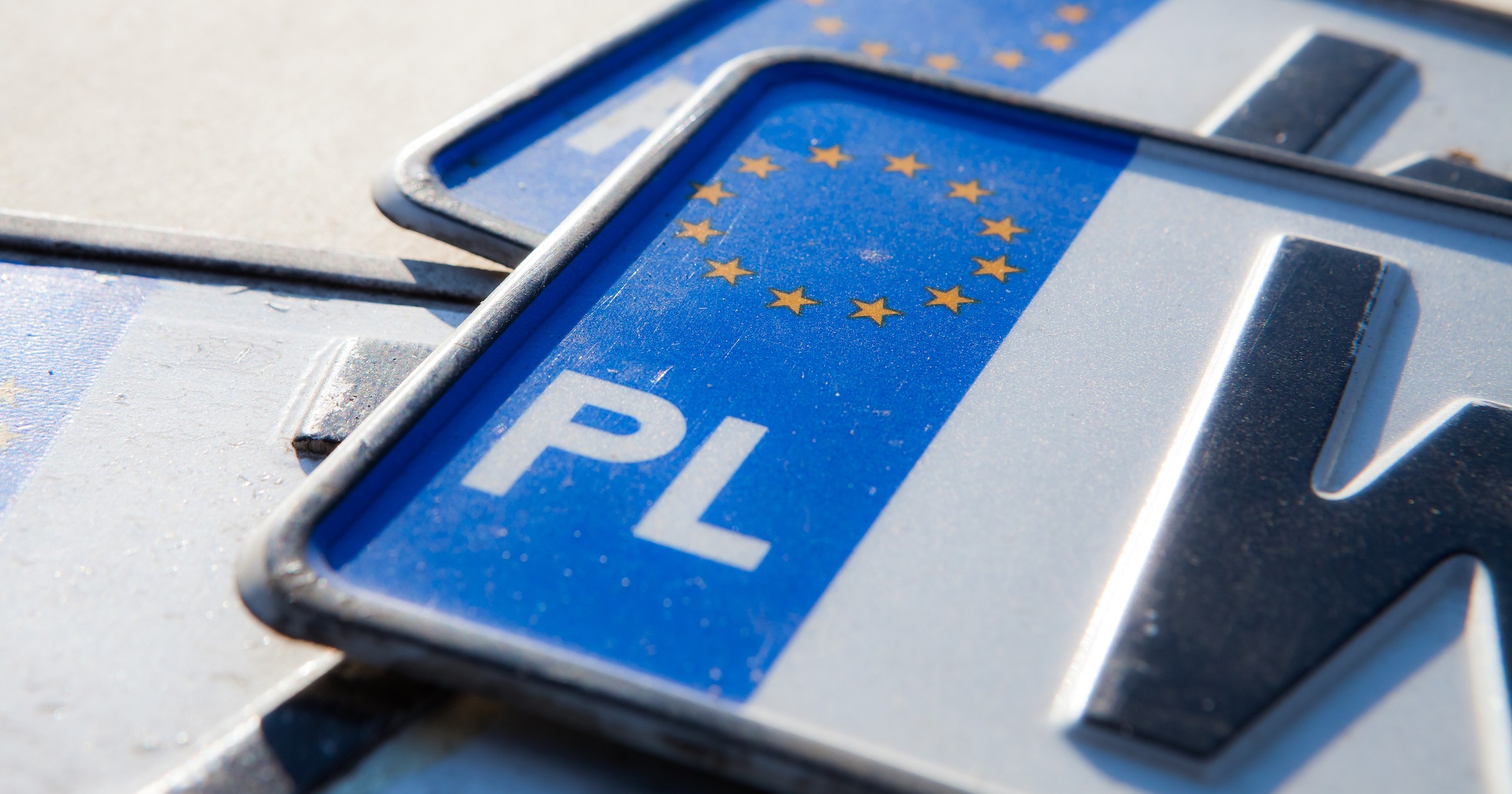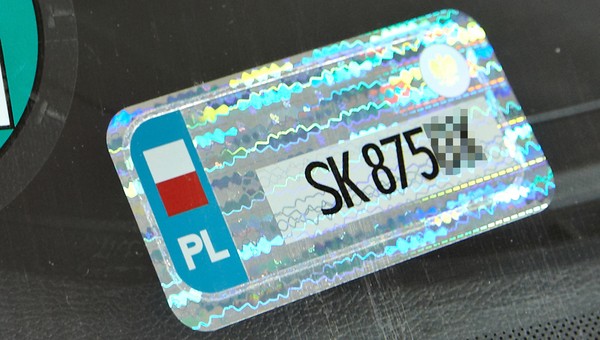
Producenci tablic proponują zmianę wzoru czcionki i nowe kolory
Skąd nagle taka troska producentów tablic o wzór czcionki? Oficjalnie chodzi, m.in. o poprawę bezpieczeństwa, ograniczenie oszustw z tablicami rejestracyjnymi i... zwiększenie ich trwałości. Ale czy faktycznie mamy aż taki problem z aktualnymi tablicami rejestracyjnymi, jak twierdzą jej producenci?
Tablice rejestracyjne - czy naprawdę mamy takie problemy?
Według Sławomira Skwarka, posła Prawa i Sprawiedliwości, najwyraźniej tak, bo parlamentarzysta skierował do Ministra Infrastruktury interpelację, w której przedstawia plan usprawnień, cyt. "w zakresie wyglądu i funkcjonalności tablic rejestracyjnych".
Tak właściwie to wniosek, który przygotowało Ogólnopolskie Stowarzyszenie Producentów Tablic Rejestracyjnych. Zarówno parlamentarzysta, jak i producenci tablic rejestracyjnych sugerują, że aktualnie dość łatwo zafałszować tablice. Jako przykład padła cyfra "8", którą podobno można bardzo łatwo przerobić na "3".
Drugą poruszaną kwestią jest problem z odczytywaniem tablic przez systemy automatyczne (maszynowe), takie jakie stosuje się w systemie poboru opłat drogowych czy fotoradarach. Podobno aktualnie pojawia się problem z odróżnieniem litery "O" od cyfry "0".
Ponadto, jak czytamy w interpelacji, nowy grubszy font liter pozwoliłby zwiększyć powierzchnię dla przyczepności folii, którą pokrywane są przetłoczenia, a tym samym zwiększy nie tylko czytelność, ale także ich trwałość. Swoją drogą, czy faktycznie istnieje problem z ich trwałością?
To jednak nie koniec. OSPTR proponuje również wprowadzenie nowej odmiany tablicy rejestracyjnej do oznakowania ciągników rolniczych, która wyróżniałaby się od tablic motocyklowych – z pomarańczowym tłem. Miałoby to zapobiec oszustwom, czyli przekładaniu w sezonie żniw tablic motocyklowych na niezarejestrowane sprzęty rolnicze, ale także zwiększyć widoczność wolniej poruszających się maszyn na drodze, a tym samym poprawić bezpieczeństwo. Z pierwszym argumentem trudno nam dyskutować, bo nie znamy statystyk, ale drugi wydaje się już nieco naciągany, bo czy trzeba poprawiać przy pomocy małej tablicy rejestracyjnej widoczność pojazdu, który jest dwa-trzy razy większy od przeciętnego samochodu?
Ostania deska ratunku?
Czytając interpelację, trudno nie odnieść wrażenia, że sam poseł Skwarka nie do końca wierzy w poruszane w niej problemy. Wszak już na samym początku niejako przechodzi w rolę narratora i podkreśla, że to wnioski zrzeszenia producentów tablic rejestracyjnych.
Dlaczego jednak po tylu latach od wprowadzenia aktualnego wzoru tablic ich producenci stwierdzili, że wymagają one gruntownej zmiany? Odpowiedź wydaje się oczywista - już za kilka miesięcy w życie wejdą przepisy, które skończą z wymianą tablic przy rejestracji auta używanego. Jak łatwo się domyślić, to potężny cios dla producentów i znaczny spadek zamówień z wydziałów komunikacji.
Być może producenci tablic liczą na to, że w nowych przepisach znalazłby się zapis zmuszający kierowców do wymiany starych "blach"? To tylko przypuszczenia, ale jeśli okazałyby się prawdziwe, to nawet jeśli zadanie to rozłożono by na kilka lat, taki scenariusz zapewne pozwoliłby przedłużyć funkcjonowanie wielu firm zajmujących się dziś tłoczeniem tablic rejestracyjnych. Z drugiej strony wprowadzenie nowego wzoru zatrzymałoby wprowadzenie nowych przepisów – tablice po zakupie auta używanego przez pierwsze lata trzeba by wymieniać i tak, bo nie odpowiadałyby nowym wzorom. Tu trzeba zaznaczyć, że to tylko nasze przypuszczenia.
W pełni rozumiemy punkt widzenia OSPTR, tym bardziej że pierwszym celem stowarzyszenia, jaki wypisano chociażby na jego stronie, jest przede wszystkim "dbanie o interesy wytwórców tablic rejestracyjnych działających w oparciu o istniejące normy prawne". Tylko mamy wątpliwości, czy na "odprawę" dla tej mocno poszkodowanej nowymi przepisami branży powinni zrzucać się kierowcy?